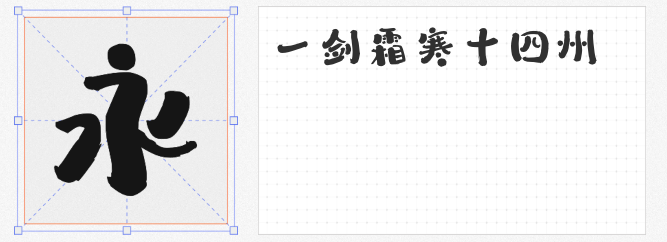
当传统书法遇见现代设计,毛笔字体便成了承载文化记忆的视觉容器。今次精选四款国潮毛笔字体,它们以水墨为骨,以气韵为魂,在点画流转间构建出东方美学的当代表达。
1.云书法玉兰行楷体
这款字体如春风拂面,主笔遒劲如松枝,块面分明似玉兰花瓣。运笔时提按顿挫的韵律感,让笔画生出"屋漏痕"般的自然意趣。特别适合文创礼盒题字,笔锋转折处的牵丝连带,恰似宣纸上晕开的墨痕,让"国潮"二字在笔势飞白间有了具象表达。
2.龙书法勘亭流风
取法江户时代勘亭流书法精髓,却以现代构成解构传统。圆润字形如满月当空,敦厚笔画似古寺铜钟,布白饱满如年画配色。用于日式料理店招牌时,既能传递"和食"的禅意,又带着赛博朋克的霓虹光影;落在国潮海报上,则让传统纹样与现代几何达成微妙对话。
3.造字侠醉春风简繁 苍劲
笔锋如醉客舞剑,在法度与放浪间游走。圆润点画似江南烟雨,苍劲主笔如北国松涛,结体在严谨骨架中透出慵懒意态。用于茶饮包装设计,能让"碧螺春"漾出茶汤清韵;印在潮玩包装上,则让机甲战士平添水墨画般的诗意。
4.万人字造昊仔体 大粗
粗犷笔画如斧劈山岩,纤细横画似竹枝摇曳,形成视觉的戏剧张力。重心下沉的设计如武士扎马步,既稳若泰山又蓄势待发。这套字体天生带着街舞的节奏感,用于音乐节海报能传递低音炮的震撼,印在国潮T恤上则让书法与街头文化碰撞出火花。
四款字体如同四幅水墨长卷,它们让传统文化不再是博物馆里的标本,而是跃动于潮流尖端的生命体。